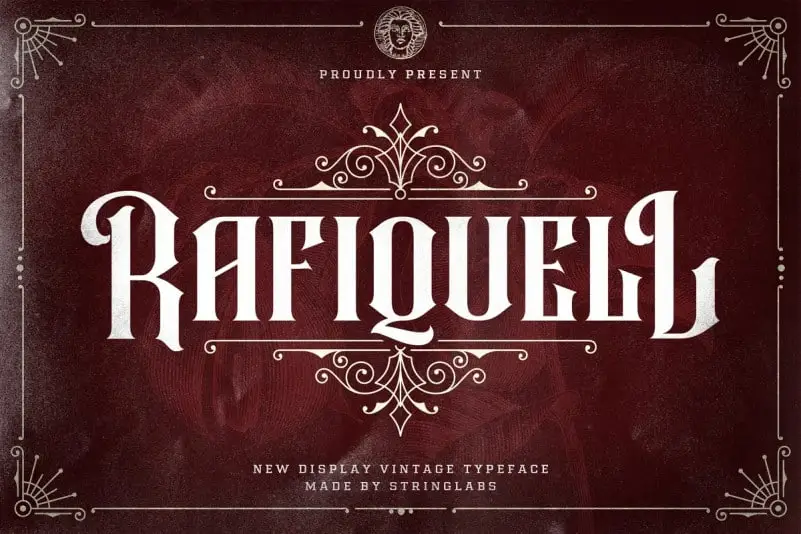
Rafiquell Display Font
Rafiquell Display Font é uma exuberante opção para aqueles que buscam um estilo vintage elegante. Este tipo-fonte foi criado pela StringLabs e inspira-se nos desenhos de tatuagem vintage, oferecendo uma aparição romântica e ousada. Rafiquell traz ao seu design moderno ou clássico uma sensação nostálgica e um formato atento aos detalhes que certamente o destacará. A fonte tem um tom único, com alternativas únicas e versáteis que vão desde nomes de loja até designs publicitários, tornando-o um recurso gráfico ideal para criar ambientes memoráveis, tanto em interfaces digitais quanto em materiais impressos. Não apenas atraente visualmente, Rafiquell também oferece uma experiência completa, combinando o elegante com o nostálgico, perfeitamente adaptado para criações que querem transmitir um sentimento de nostalgia e originalidade ao mesmo tempo.